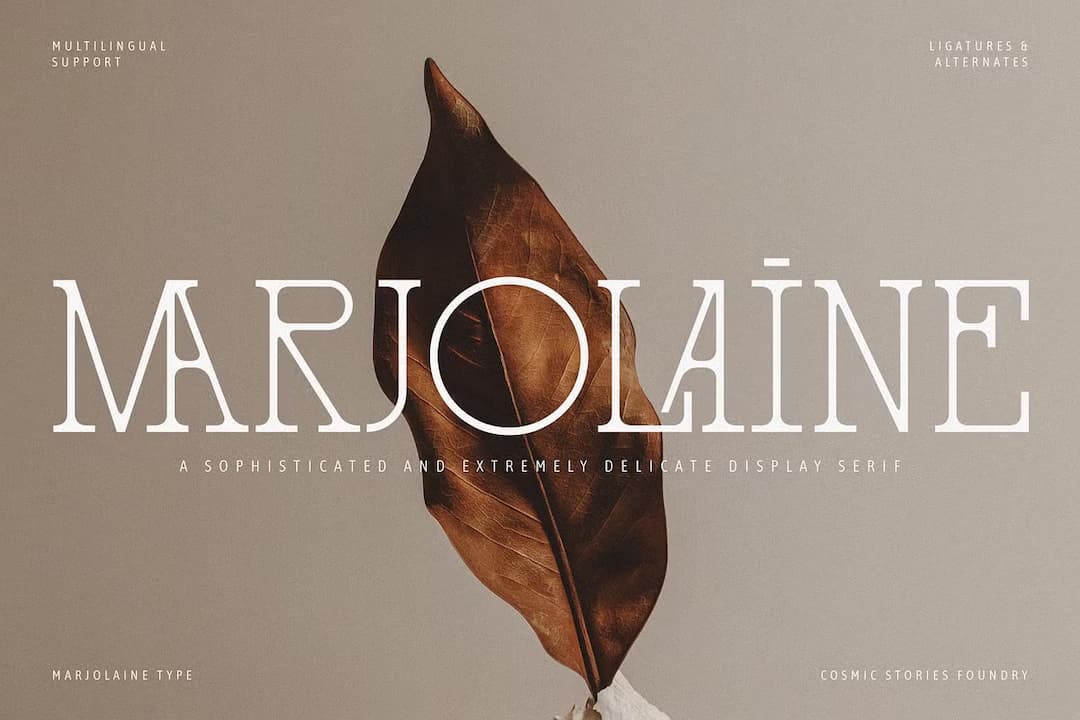
Set Sail Studios
Marjolaine
シックなスラブセリフディスプレイ。この手としてはめずらしいスラブセリフが元となっており、グリフはジオメトリックかつタイプライター風味があり、ボウルを持つ字以外は結構コンデンスなプロポーションに押し込まれている。ウェイトは軽く、e のバーが斜めになっているなどシックかつエレガントな雰囲気を持っており、リガチャーも60種近くあって面白い文字組が楽しめる。ディスプレイやロゴデザインで重宝するだろう。名前はマルジョレーヌもしくはマヨラナと読み、地中海産のハーブの事らしく、同名のケーキやランジェリーブランドなどが見つかった。1ウェイトのみ。